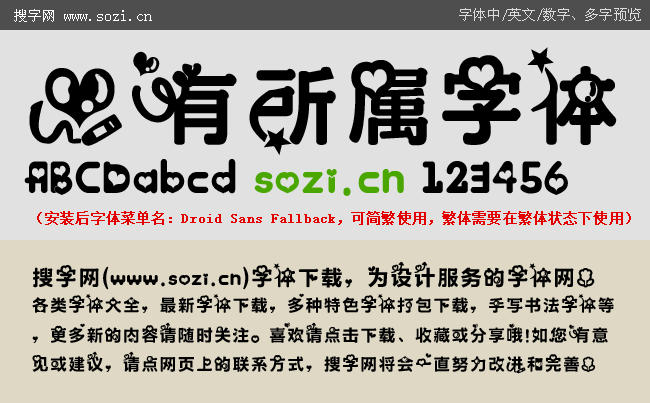
心有所屬字體
搜字網(wǎng)給大家提供一款很有趣的手機(jī)中文字體下載。修改者給他起名為心有所屬字體,這款手機(jī)字體是在粗圓體字體為原形,字體的筆畫進(jìn)行了卡通變化,筆畫間又點(diǎn)綴了可愛的卡通圖案。在具備粗圓字體醒目清晰端正的風(fēng)格同時(shí),卡通味也特別濃,是一款非?蓯鄣目ㄍㄗ煮w,特別適合喜歡手機(jī)字體個(gè)性一些的朋友在手機(jī)上安裝使用。